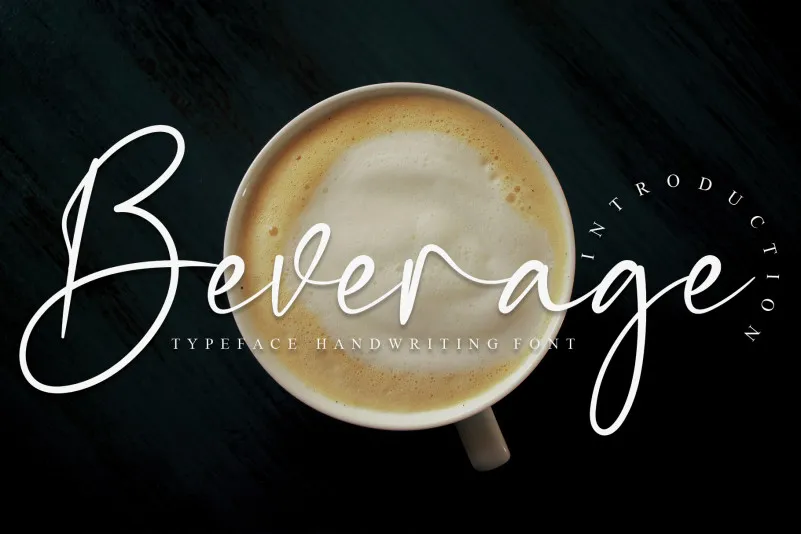
A fonte Beverage Script Font oferece uma experiência única para designers que desejam adicionar um toque delicado a seus projetos digitais. Feita por creativeletter, essa elegante fonte à mão livre é perfeita para criações que exigem personalidade e sofisticação sem comprometer o resultado final. Com linhas suaves e detalhes meticulosamente cuidados, a Beverage Script Font permite criar texturas e bordas vibrantes em qualquer aplicação do seu design. Ideal tanto para nomes de marca quanto para capas de livros e cartões de visita, ela oferece uma opção única que combina com diversos estilos e formatos gráficos. Seja você um designer profissional ou iniciante, Beverage Script Font se torna uma ferramenta indispensável para quem procura aperfeiçoar sua marca visual ou produzir projetos de arte digital impressionantes.